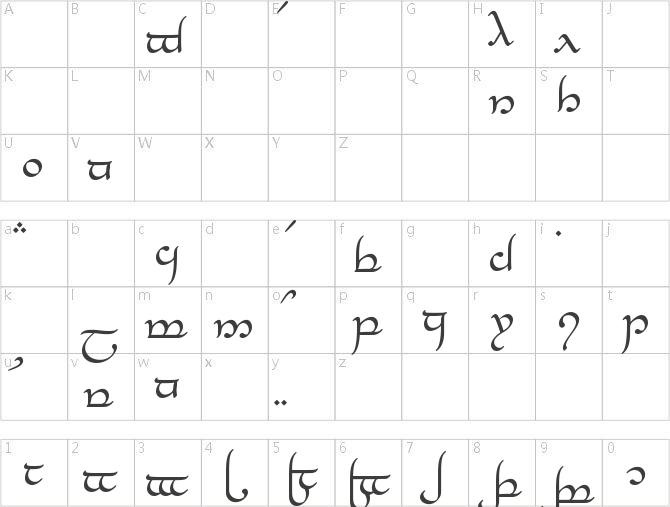
字體名稱(chēng): Tengwar
Tengwar-Elesil-Normal
Tengwar-Elesil-Normal介紹
Tengwar-Elesil-Normal字體字庫(kù)是一款讓人賞心悅目、百看不厭的英文字體,適合各類(lèi)廣告和產(chǎn)品包裝設(shè)計(jì)應(yīng)用,字體大小0.02MB,格式為ttf字體,上傳用戶(hù)是漫步云端,作者/版權(quán)方為未知